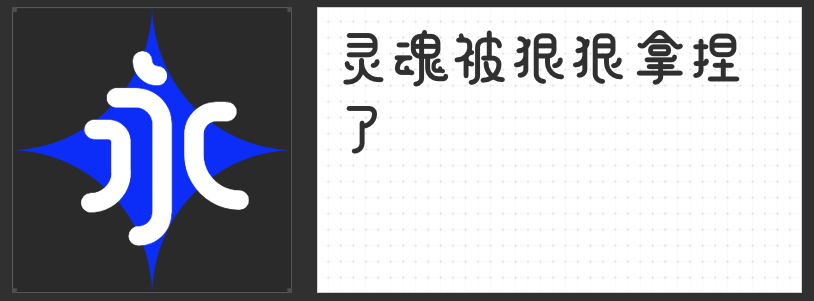
影视设计字体推荐:四款风格化字体唤醒视觉叙事
在影视设计的视觉语言体系中,字体不仅是信息载体,更是情绪与氛围的延伸。当画面需要传递俏皮、灵动或温暖的情感时,一款风格契合的字体往往能成为点睛之笔。以下四款字体以独特的设计语言,为影视标题、字幕或动态图形注入鲜活的生命力。
一、励字敲可爱简 常规
这款字体以手写感为基底,通过圆润的线条与简化的笔画结构,营造出孩童涂鸦般的纯真感。其省略部分笔画的设计并非随意为之,而是在保留辨识度的前提下,以“不完整”的形态传递随性自然的情绪。笔画转折处的微妙弧度与灰度均匀的笔触,既保留了手写的柔软质感,又避免了过度装饰的杂乱感。在需要传递轻松、治愈氛围的影视场景中,这款字体能以“不刻意”的姿态拉近与观众的距离。
二、字恋狂漫野 摇风
以直线为基础的笔画设计,通过“断开”与去钩处理打破传统字体的机械感,赋予文字呼吸般的灵动性。字型大小错落的布局与通透的布白空间,形成视觉上的节奏起伏,仿佛文字在画面中自然生长。灰度均匀的笔触与简洁的线条结构,使其在动态效果中能保持清晰的识别度,尤其适合需要强调文字运动轨迹的片头设计或字幕动画。
三、字恋狂嗨玩简
粗壮的笔画与方块字形构建出类似积木的视觉形态,重心下沉的设计强化了字体的稳定感,而圆角与钝角的搭配则巧妙中和了笨拙感,转化为令人忍俊不禁的可爱气质。这款字体在影视设计中可作为角色昵称、儿童向内容标题或喜剧场景的点缀,其夸张的形态能瞬间激活画面的趣味性。
四、字恋狂丸粒简
笔画两端的圆角处理与圆头圆尾的设计,赋予文字棉花糖般的柔软质感。这种无棱角的形态天然具有亲和力,能弱化文字的攻击性,在科幻、奇幻或家庭题材影视中,可作为副标题或说明文字,以温和的视觉语言平衡画面的科技感或冲突感,营造情感共鸣的缓冲空间。
影视设计的字体选择,本质是视觉情绪的精准投射。四款字体以差异化设计语言,为影视创作者提供了丰富的情绪表达工具。当文字形态与画面叙事同频共振,视觉语言便拥有了穿透屏幕的力量。